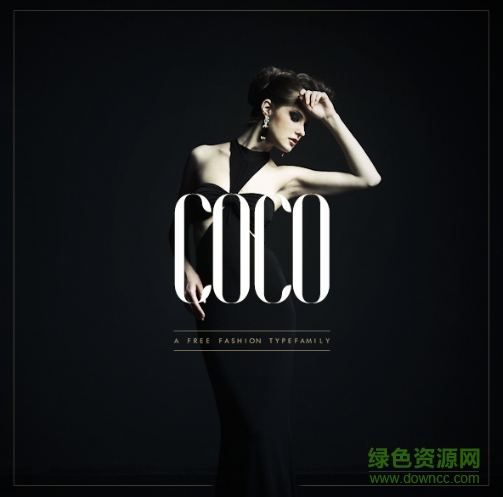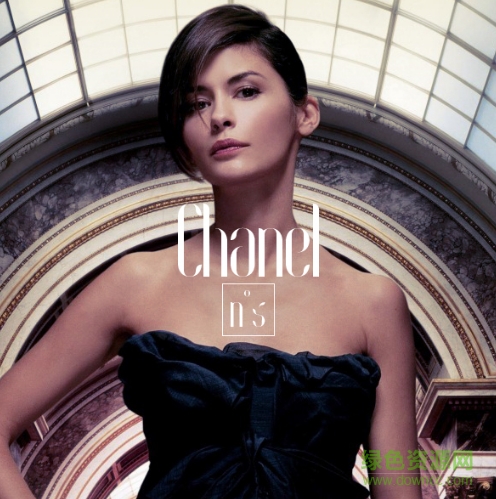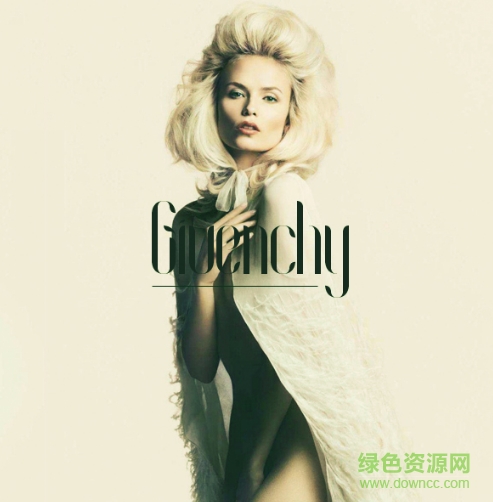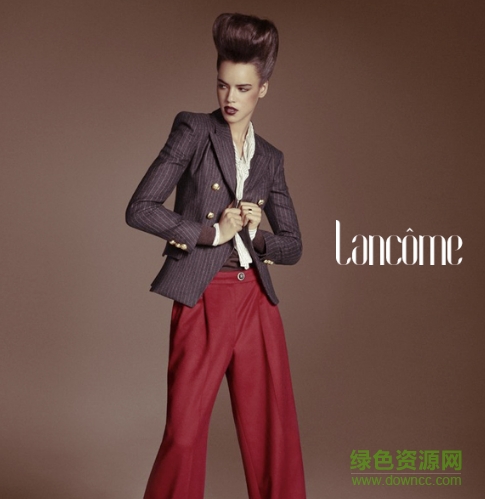
Coco時(shí)尚字體是廣告和平面設(shè)計(jì)常用的一款字體,它屬于無襯線字體,在設(shè)計(jì)一些英文字時(shí),可別小看了它們,它能幫你的大忙,讓你的設(shè)計(jì)別出心裁,小編這里分享了Coco-Bold.otf、Coco-BoldItalic.otf、Coco-Italic.otf等8款字體,希望大家喜歡。
Coco是無襯線字體家族的一員,整套字型精減為八種:常規(guī),斜體,粗體,斜粗,緊縮,緊縮斜體,緊縮粗體和緊縮斜粗,可用于包含多種字形的數(shù)字和印刷項(xiàng)目中。其中每種字型又各有超過209個(gè)字形,包括小寫字母,大寫字母,數(shù)字,特殊符號(hào)以及標(biāo)點(diǎn)。這一整套非常適合那些想強(qiáng)調(diào)作品時(shí)尚特點(diǎn)的字體愛好者們。